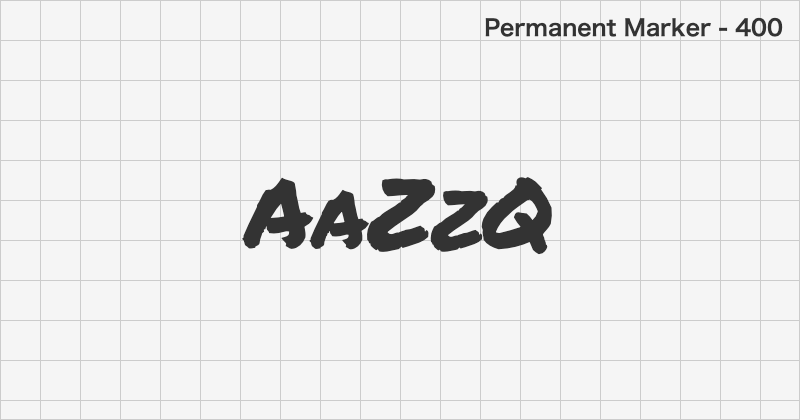
Permanent Marker – 商用利用できる手書きフリーフォント
Permanent Marker は、お気に入りの筆記具の見た目と感触を再現したフォントです。
Permanent Marker は、アメリカのタイプファウンドリー Font Diner によってデザインされ、筆記具の特徴を活かした表現が求められる場面に適しています。